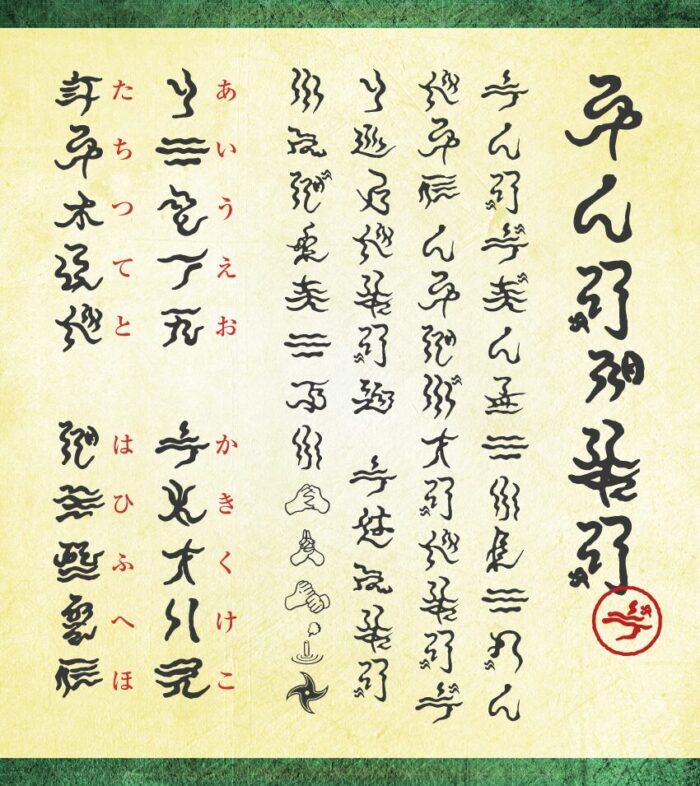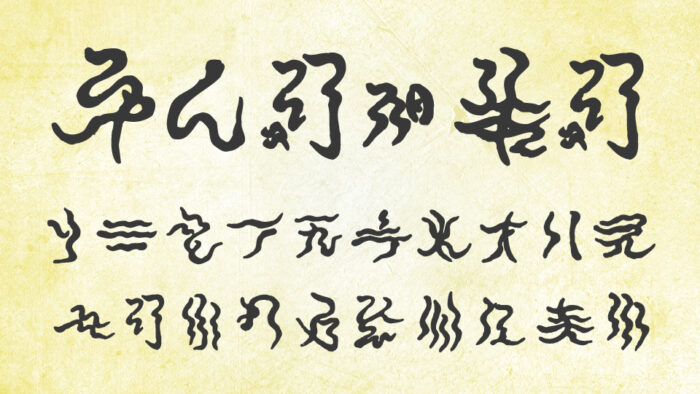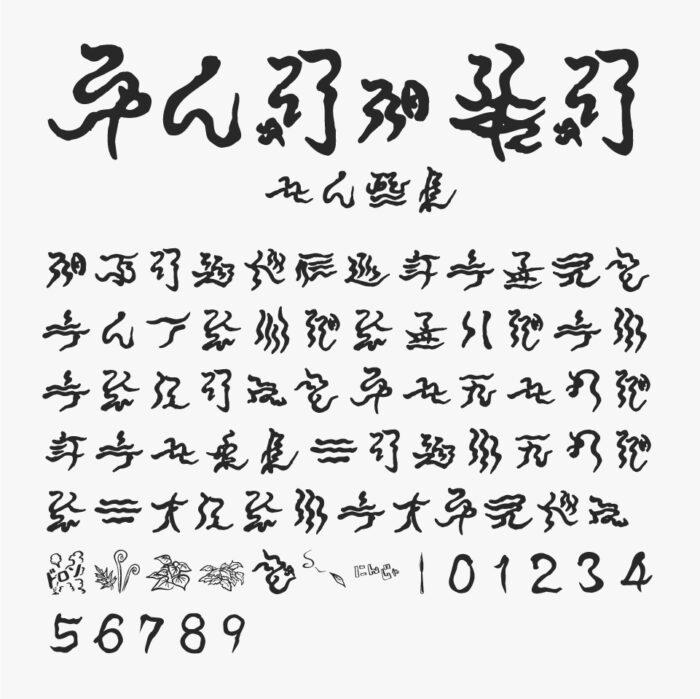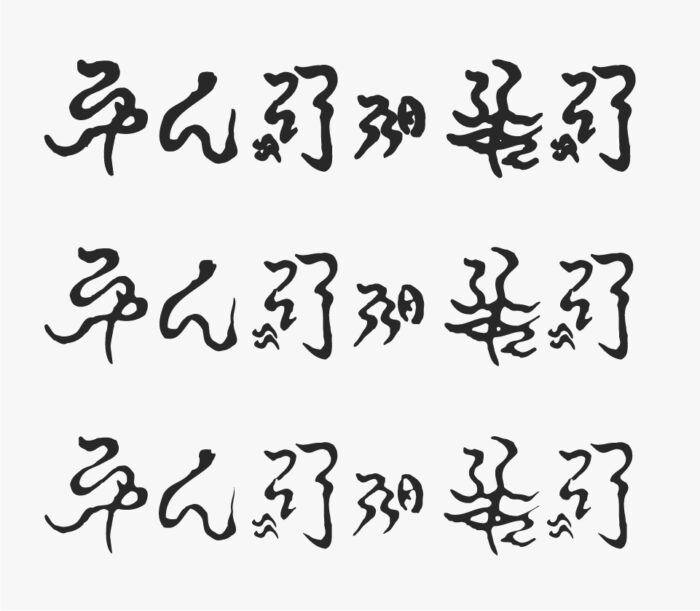
忍者文字
忍者文字フォントは、伊賀忍者で有名な三重県伊賀市の上野商工会議所観光部会が制作した「神代文字」を再現したフォントです。
漢字が伝来する以前の日本には独自の文字がありその文字を「神代文字」と呼ばれています。忍者が活躍していた戦国時代には解読できる者がいなく、「神代文字」を忍者はこれを利用し、秘密文字として連絡手段に使用していたといわれています。(※諸説あり)
忍者文字
忍者が本当に使っていたのかなと思うとなんだかロマンがありますね。筆のような質感や、ゆらぎのある文字がとっても世界観があり、とても素敵です。
忍者や巻物などのビジュアル制作する際にもぴったりなフォントです。
ウェイトも「Light」「Mediam」「Bold」の3種類用意されています。
収録文字は、ひらがな・数字・記号が収録されています。
カタカナ×
漢字×